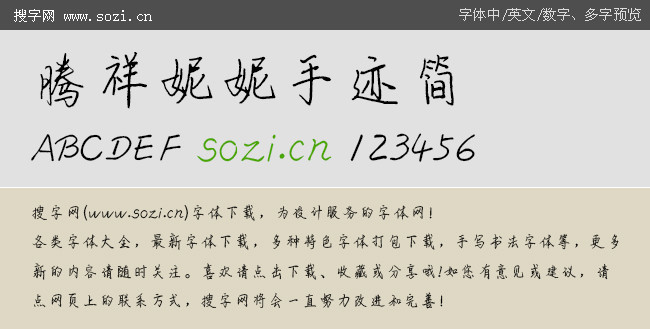
騰祥妮妮手跡簡(jiǎn)
搜字網(wǎng)提供一款騰祥妮妮手跡簡(jiǎn)中文藝術(shù)字體下載,騰祥妮妮手跡簡(jiǎn)是一款很漂亮的手寫(xiě)字體,書(shū)寫(xiě)風(fēng)格自然流暢,獨(dú)具風(fēng)格,稚拙中透顯出活潑靈動(dòng)的氣息;無(wú)雕琢,無(wú)拘束質(zhì)樸的視覺(jué)效果,用于正文更體現(xiàn)出手寫(xiě)自然之感。字體可以廣泛應(yīng)用于印刷出版、包裝設(shè)計(jì)、廣告設(shè)計(jì)、網(wǎng)頁(yè)設(shè)計(jì)等領(lǐng)域。